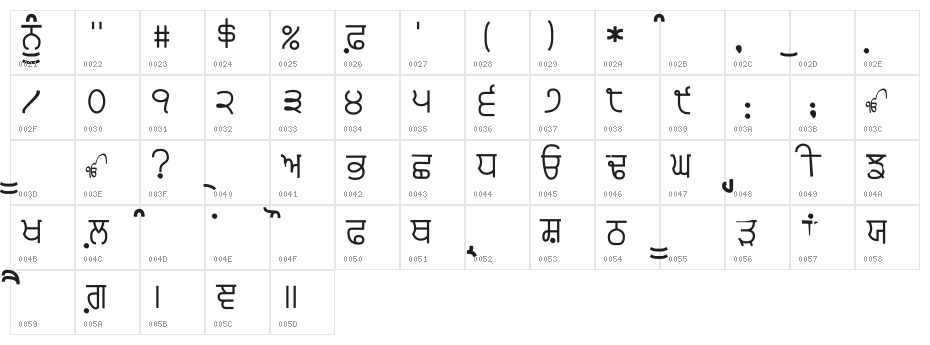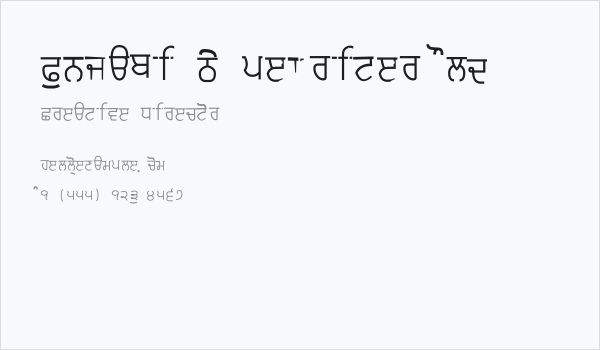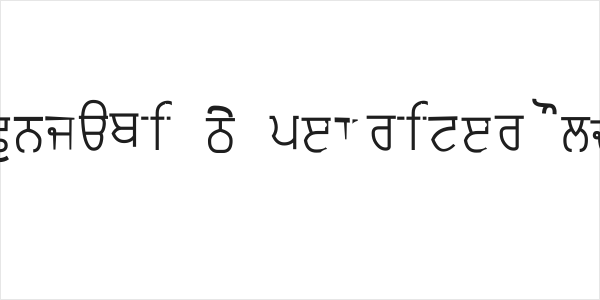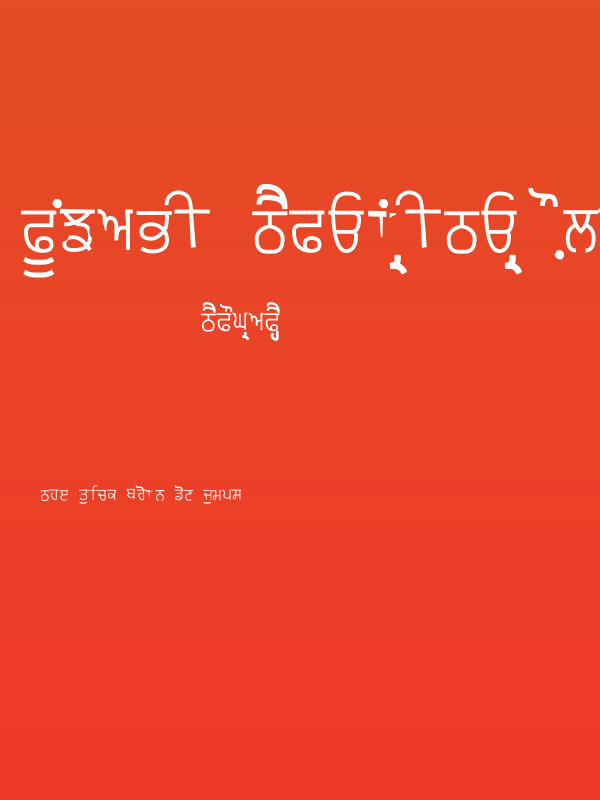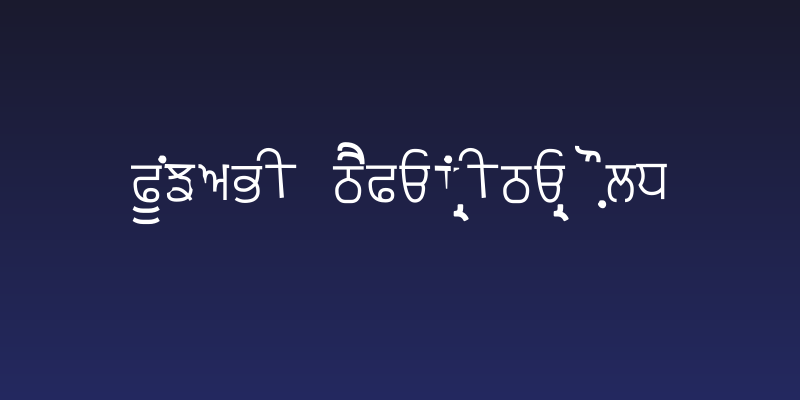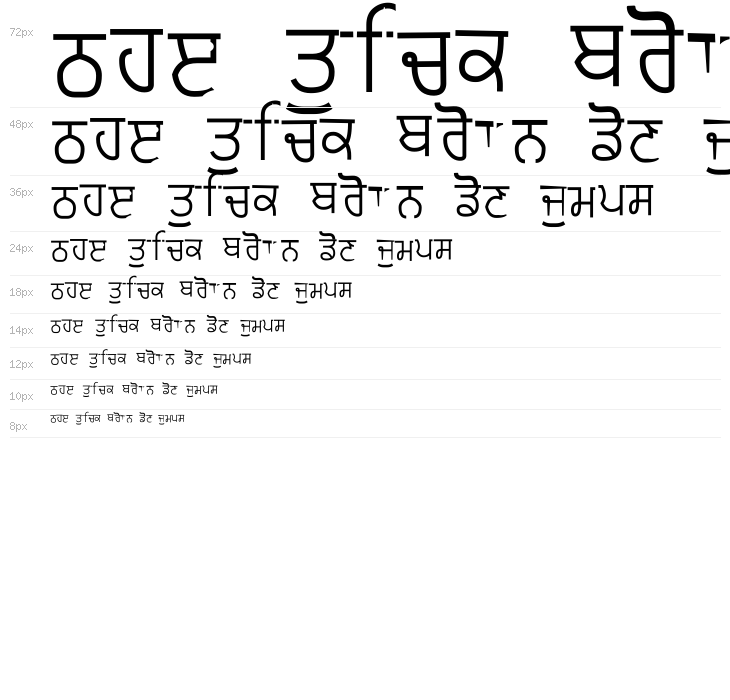
Punjabi Typewriter Old Font
| 整体风格 | Classic |
| 使用场景 | Body text, Documents |
| 推荐项目 | Ideal for creating documents in Punjabi, educational materials, or any project requiring a traditional typewriter aesthetic. |